「強靱」「靱帯」などの語で使われる「靱」にはバリエーションが多く、字体おたく的には話が長くなりがちな例なのですが、ばっさり削って図には2つだけ並べました。
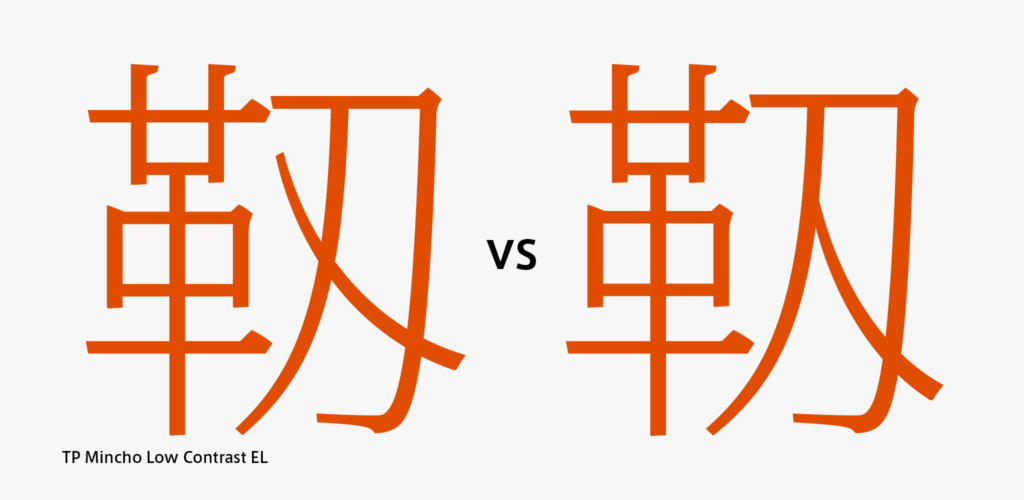
皆さん、なじみがあるのはおそらく左のほうではないでしょうか。右のほうは、一時期写植機の文字盤で使われていた形で、写植の時代には書籍でよく見かけました。この字体が、写植経由でJISの文字コード規格の1978年版に使用され、それから45年の歳月を経た今でも、OpenTypeフォントのグリフ置換機能によって召喚することが可能となっています。
実はこの右側の字体の「靱」はわたしのお気に入りで、いつか使ってみたいと思っているのですが、なかなかその機会が巡ってきません。このブログ記事がその機会だと言えないこともないですけど。